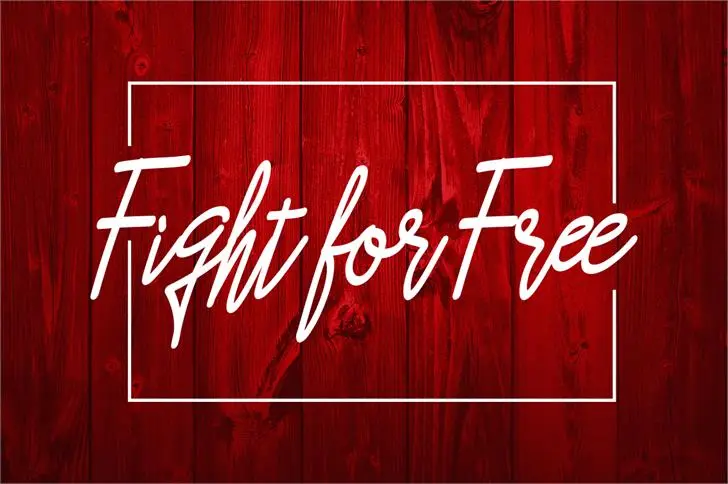
Asfrogas Font
A Asfrogas Font é uma excelente escolha para designers que procuram uma mão escrita única e vibrante. Seu designer, Hamilton, criou uma fonte que combina elegância com um toque pessoal e versátil. Ideal tanto para projetos pessoais quanto comerciais, esta fonte deixa seu trabalho em qualquer projeto imprimível ou digital. Com uso livre tanto para fins pessoais como comerciais, a Asfrogas Font é bastante flexível. Os designers podem apreciar o fato de que também aceita doações se valorizarem o trabalho do designer. Através deste link, você pode visitar o armazém da CreativeMarket e explorar uma grande variedade de outras fontes de alta qualidade disponíveis. Hamilton mantém seu público atualizado através do Instagram, onde você pode acompanhá-lo de perto e ver as novas criações que ele está desenvolvendo. A Asfrogas Font é apenas um dos muitos recursos que Hamilton disponibiliza gratuitamente para o designer e amante de arte em geral. Seja você um novo designer ou um profissional que busca aperfeiçoamento contínuo, não perca essa oportunidade única de explorar uma fonte original e incrivelmente personalizada.